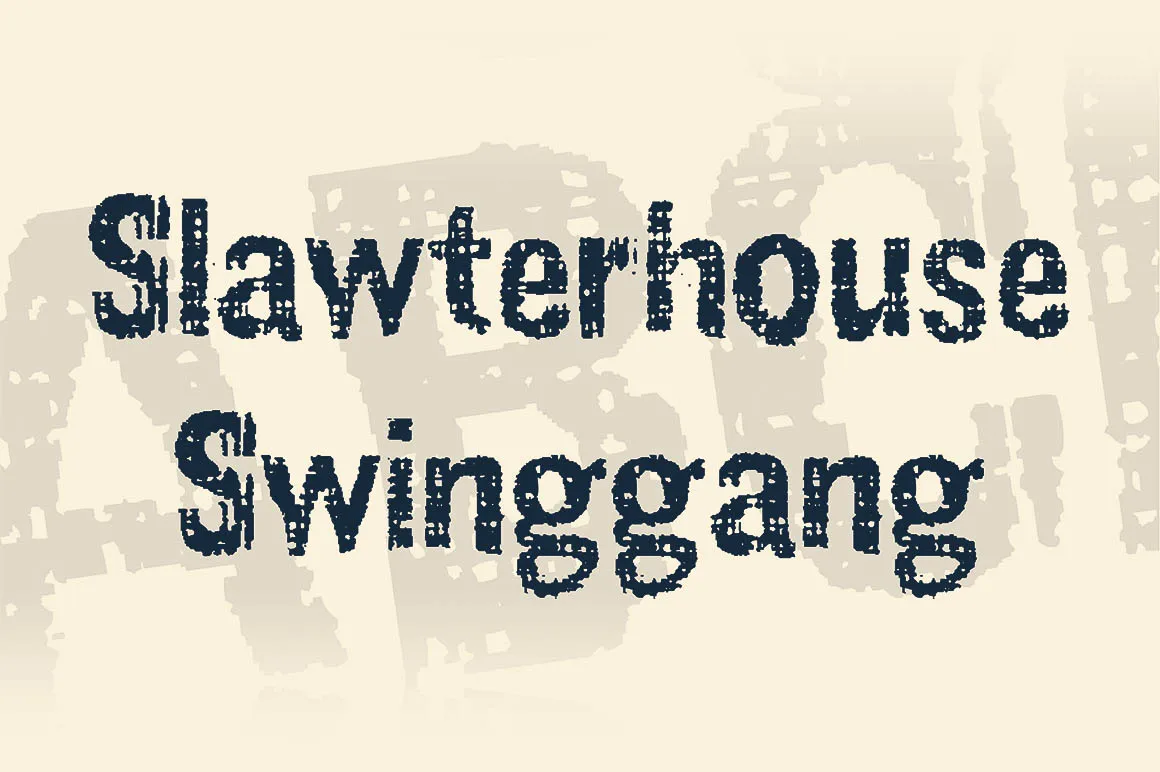
A fonte Slawterhouse Swinggang é uma criação única e cheia de grau do Hamilton, disponível no Bumbayo Font Fabrik. Perfeita para estilos criativos e descolados, esta fonte é ideal para novos projetos visuais que buscam agregar personalidade ao design. Ela combina elementos retro com um toque moderno, tornando-a uma escolha inovadora em sua categoria de fonts decorativas. Suas linhas leves e curvilíneas permitem criar texturas interessantes em qualquer obra visual, seja ela impressa ou digital. Seja para nomes de marca, ilustrações, publicidade ou artesanato, a Slawterhouse Swinggang tem um gosto único que certamente fará sua coleção de fontes mais atraente e original.